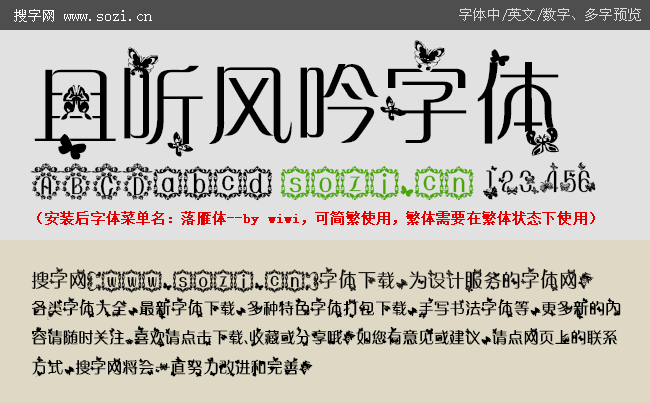
且聽風(fēng)吟字體
且聽風(fēng)吟字體是一款是由搜字網(wǎng)提供中文字體下載,其中文字體部分以蝴蝶圖形為點(diǎn)綴,英文字體則由花邊裝飾,字體唯美詩意,可用于廣告設(shè)計(jì)字體、網(wǎng)頁設(shè)計(jì)字體、包裝設(shè)計(jì)字體、 屏幕顯示字體等,有需要的朋友可以下載看看哦。